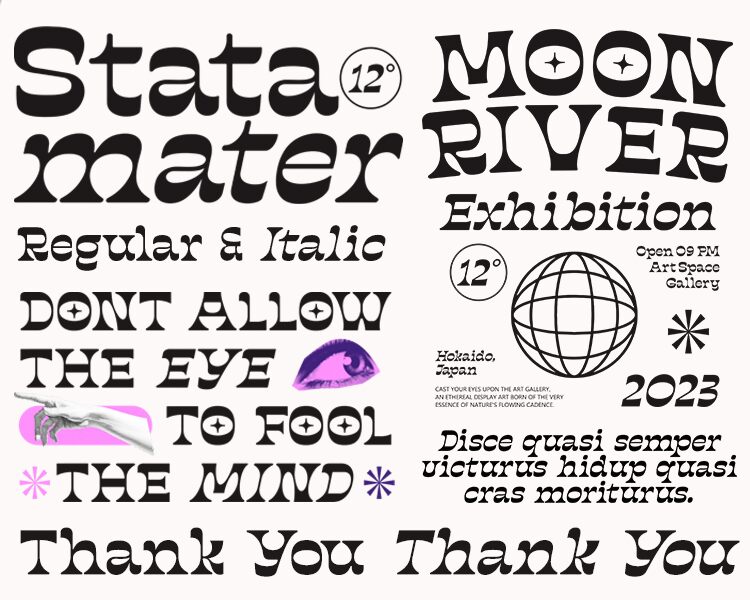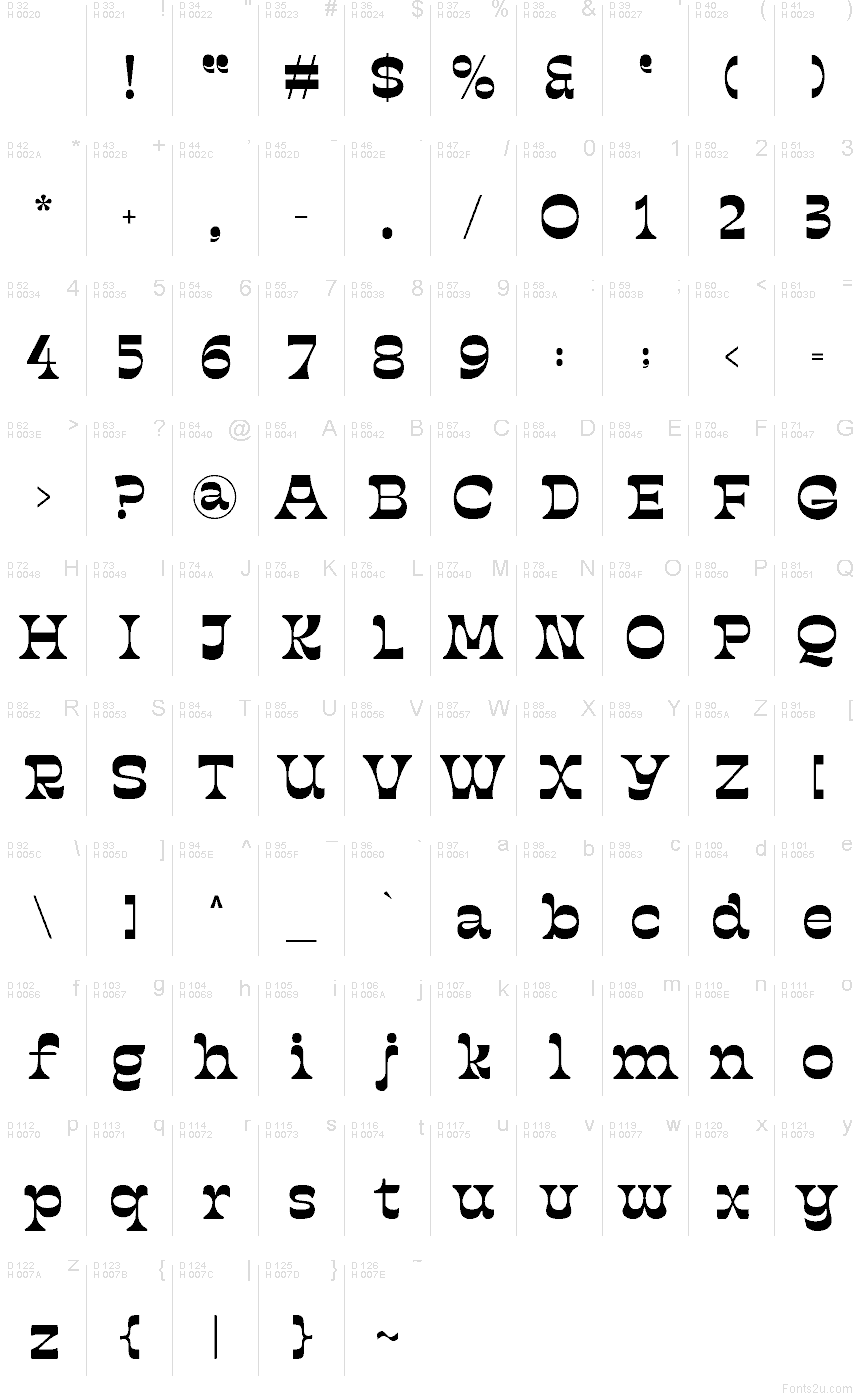
Stata Mater من تصميم Four Lines Std هو خط عرض مجاني بأسلوب "غروفي" (groovy) يتميز بأشكال دائرية ومنحنيات ناعمة وإيقاع مستوحى من حقبة السبعينيات. تبدو الحروف ذات طابع أنيق وغير متكلف، مع وصلات انسيابية وحركة هادئة تضفي على التصميم لمسة من الاسترخاء.
يعمل Stata Mater بشكل رائع على أغلفة الألبومات، وقوائم المقاهي، والملصقات، ومنشورات الفعاليات، والشعارات التي تحتاج إلى لمسة ريترو لطيفة. هذا الخط المجاني مناسب أيضًا لتصميمات التغليف، ورسومات منصات التواصل الاجتماعي، والاقتباسات القصيرة، حيث تتمتع أشكاله المنحوتة بدقة بخصائص زخرفية واضحة دون أن تبدو مزدحمة أو معقدة.